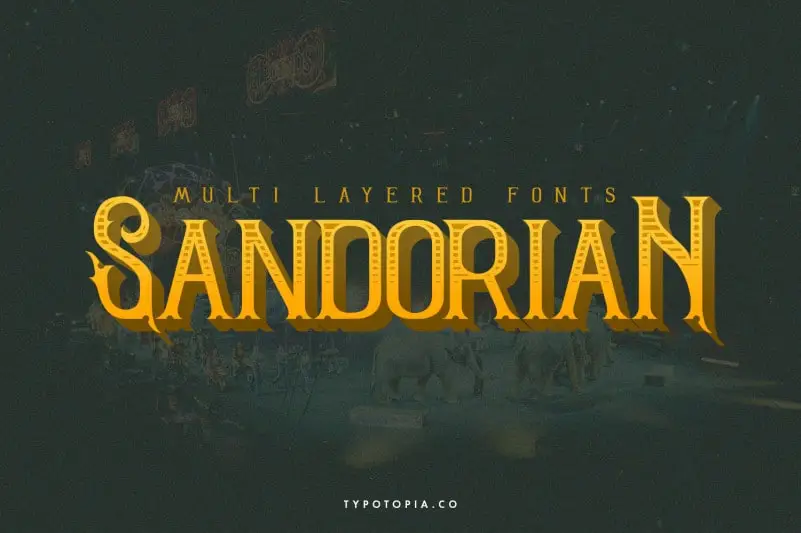
Sandorian Display Font – Download Grátis
A Sandorian Display Font é uma fonte tipo multi-layers que se inspira no estilo vintage. Esta fonte vem com sete capas ou fontes compostas, que você pode combinar. Cada combinação foi cuidadosamente elaborada para melhorar ainda mais suas criações de design. Seja você um designer de gráficos de perfil profissional ou alguém que simplesmente quer adicionar um toque vintage a seus projetos digitais, esta fonte é perfeita. A Sandorian Display oferece uma mistura única e divertida entre a elegância clássica e a modernidade atual. Seja para criar uma identidade visual impressionante ou um design de marca impecável, essa fonte está certa para você. Descubra o charme vintage que sua próxima criação gráfica pode exibir.